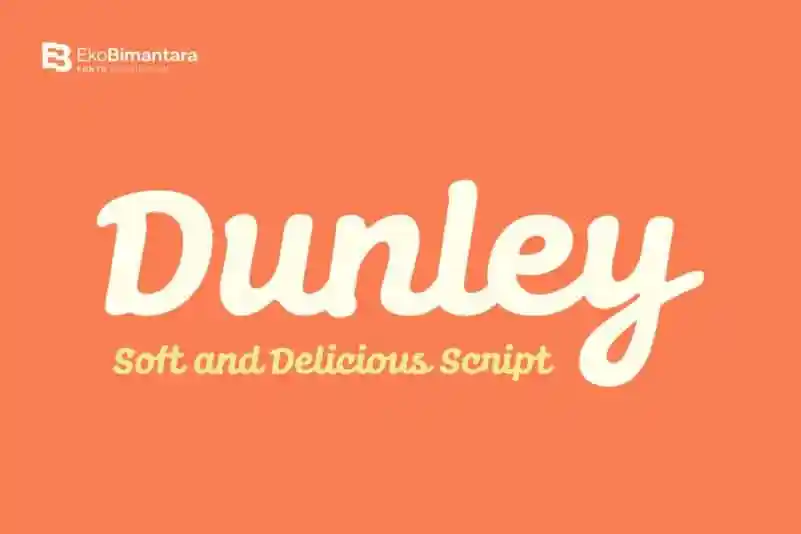
Aqui está uma versão do texto com 2 parágrafos curtos para a descrição da fonte Dunley Script Font: Dunley Script é uma fonte suave e natural, criada no estilo de escrita manuscrita. É perfeitamente adequada para um vasto espectro de projetos gráficos, incluindo marcas, títulos, logomarcas, produtos e outros. Ideal para quando você precisa dar uma cara única a seu projeto, Dunley Script tem aquela pitada de personalidade que faz todas as diferenças no ambiente visual de um design. Esta fonte do designer 99designs é ideal para quem busca uma escrita manuscrita suave e elegante. Esse estilo delicado se destaca em grandes exibições, tornando-se perfeito para marcas visuais atraentes e memoráveis. Seja você um designer de branding, criativo digital ou produtor de produto, Dunley Script será uma fonte indispensável na sua coleção de recursos gráficos.